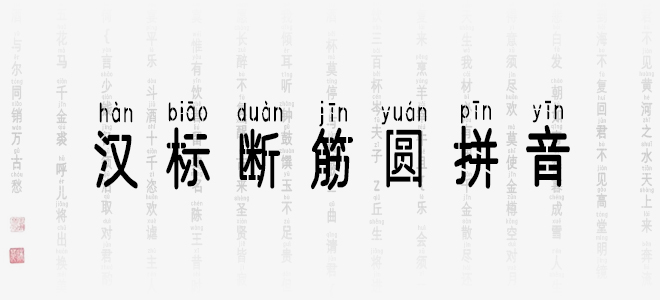
漢標(biāo)斷筋圓拼音根據(jù)圓體的字形創(chuàng)作而來(lái),作者通過(guò)大量字體截?cái)嘣O(shè)計(jì),使得字體有斷筋感,從而展現(xiàn)美術(shù)視覺(jué)感,蘊(yùn)含著深沉的藝術(shù)魅力,能給人以無(wú)限的美感,適合應(yīng)用于藝術(shù)設(shè)計(jì)、平面宣傳、包裝印刷、圖形設(shè)計(jì)、網(wǎng)頁(yè)設(shè)計(jì)、書法字帖等領(lǐng)域。歡迎喜歡此字體的朋友前來(lái)下載使用。
漢標(biāo)斷筋圓拼音